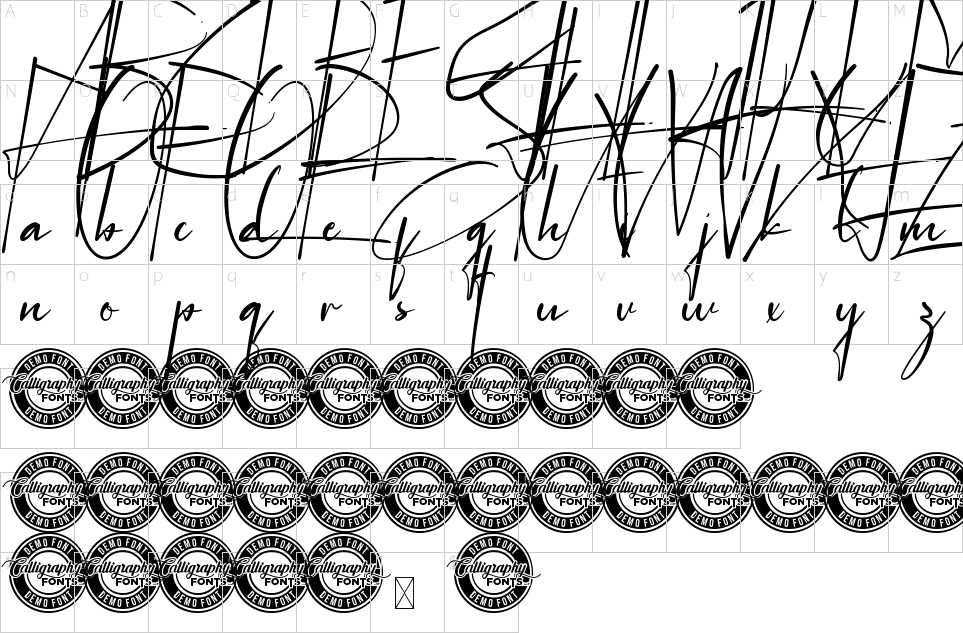
Descubra a essência do design na sua próxima missão criativa com a Janitra Kamala Font. Desenhada pela incrível Calligraphyfonts, esta fonte oferece uma escolha versátil para qualquer projeto de design gráfico. Com suas linhas suaves e elegantes, você pode transmitir uma mensagem profunda ou criar um design sofisticado em apenas uma pequena mudança na disposição das letras. Janitra Kamala foi projetada para atender a necessidade de designers que desejam incorporar um toque de caligrafia à sua obra. Com sua facilidade de uso e alegria gráfica, ela também é perfeita para os estilistas digitais em busca de uma fonte única e expressiva. A Janitra Kamala é uma excelente escolha para quem procura recursos de design gratuitos, oferecendo a você um amplo leque de opções. Seja para títulos ou texto interno, este design cuidadosamente criado pelo Calligraphyfonts oferece uma conexão única entre a escrita e o design visual. Seja você designer gráfico profissional ou iniciante, a Janitra Kamala é o acessório perfeito que irá tornar seus trabalhos mais expressivos. Descubra-se com esta fonte livre de direitos autorais hoje.